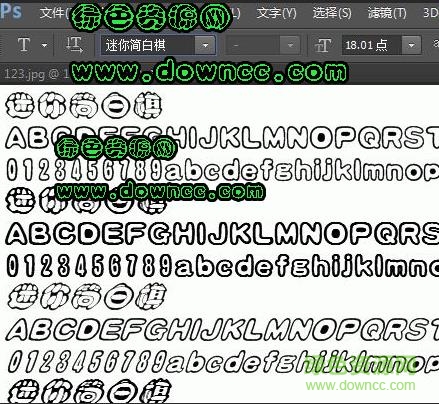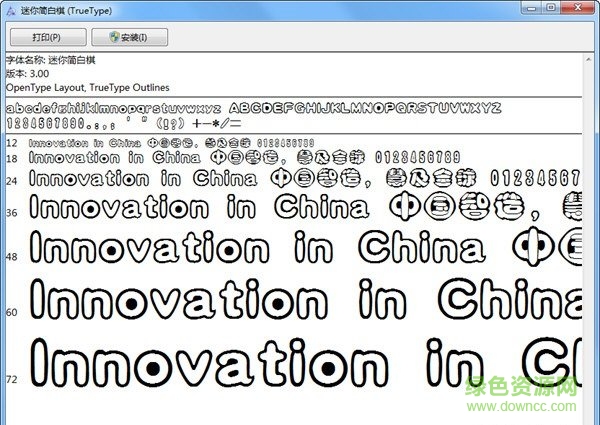
迷你簡(jiǎn)白棋字體是一款十分可愛(ài)的原型體字體,擁有原型的字體風(fēng)格,讓你在各類動(dòng)漫制作或者字幕制作的時(shí)候都能夠收到良好的反響,廣受用戶的喜愛(ài)!
迷你簡(jiǎn)白棋字體是一款典型的圓形字體,字體書(shū)寫(xiě)完成后會(huì)呈圓形,特別卡通和可愛(ài)。